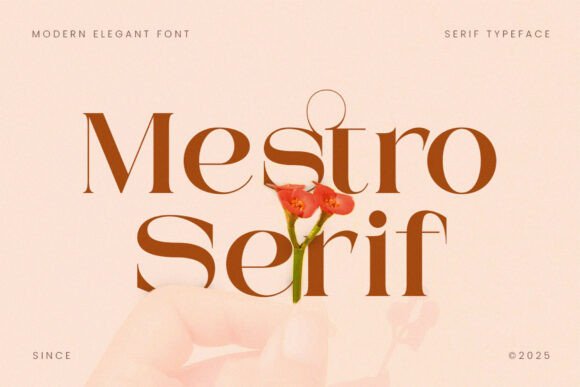
Mestro Serif Modern Ligature
Việc tìm kiếm các thành phần thiết kế phù hợp có thể là một thách thức, nhưng Mestro Serif Modern Ligature cung cấp một bộ sưu tập đặc biệt giúp nâng tầm công việc của bạn ngay lập tức.
Cho dù bạn đang tạo sản phẩm POD (In theo yêu cầu), thiệp mời đám cưới hay đồ họa mạng xã hội, Mestro Serif Modern Ligature đều là một sự lựa chọn lý tưởng.